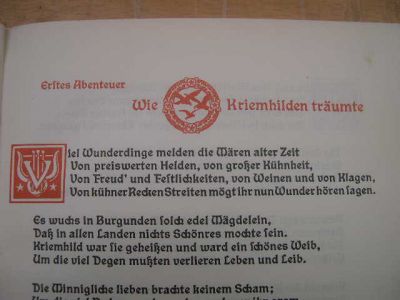
Überarbeitete Neuedition – wieviel ändern? (war: Warum sieht
Spin-Off aus dem Diskussionsstrang »warum sieht die fraktur aus, wie sie aussieht?«
Aber meine Ansicht: Ein Text aus der Zeit, in der Fraktur üblich war, sollte (wenn er es denn überhaupt wert ist) auch im Original zugänglich bleiben. Klar wird bei zunehmendem Zeitabstand die Frage immer wichtiger, wo eine "behutsame" Überarbeitung (so bezeichnet in üblichen Vorwortformulierungen) nötig ist, um eine normale Rezeption zu ermöglichen. Aber dann müssen doch weiterreichende Änderungen erwogen werden als ein Wechsel des Fonts. Und dazu ist eine profunde Kenntnis der Regeln der Zeit erforderlich.
Schön, dass dieses Thema hier einmal zur Sprache kommt (vielleicht könnte man die Diskussion auch separat weiterführen?). Hier wird oft von der »Zeit, in der Fraktur üblich war« gesprochen – gemeint ist aber vornehmlich die Zeit von ca. 1800 bis zum Frakturverbot. Diese Texte sind für uns ja – Fraktur hin oder her – in der Regel noch ohne weiteres verständlich. Aber was ist mit einem Text aus dem Mittelalter? dem Barock? Lesen die Original-Fetischisten hier tatsächlich auch ihren Machiavelli, ihren Shakespeare, ihren Molière oder Calderón ›im Original‹?
Der durchschnittliche Leser macht sich in der Regel überhaupt keine Vorstellung, welch gewaltige Arbeit hinter einer Neuedition älterer Texte – mein Alltag übrigens – steckt. Gerade das Problem des ›Original‹ – ob Buch oder Musik – ist weitaus komplizierter, als es auf den ersten Blick scheint: In der Regel hat man ja verschiedene Versionen, Lesarten, Textstufen, Ausgaben, Varianten etc. – die Frage nach dem Layout oder der Schrifttype ist da noch eine der einfachsten.
Schön, dass dieses Thema hier einmal zur Sprache kommt (vielleicht könnte man die Diskussion auch separat weiterführen?). Hier wird oft von der »Zeit, in der Fraktur üblich war« gesprochen – gemeint ist aber vornehmlich die Zeit von ca. 1800 bis zum Frakturverbot. Diese Texte sind für uns ja – Fraktur hin oder her – in der Regel noch ohne weiteres verständlich. Aber was ist mit einem Text aus dem Mittelalter? dem Barock? Lesen die Original-Fetischisten hier tatsächlich auch ihren Machiavelli, ihren Shakespeare, ihren Molière oder Calderón ›im Original‹?
Der durchschnittliche Leser macht sich in der Regel überhaupt keine Vorstellung, welch gewaltige Arbeit hinter einer Neuedition älterer Texte – mein Alltag übrigens – steckt. Gerade das Problem des ›Original‹ – ob Buch oder Musik – ist weitaus komplizierter, als es auf den ersten Blick scheint: In der Regel hat man ja verschiedene Versionen, Lesarten, Textstufen, Ausgaben, Varianten etc. – die Frage nach dem Layout oder der Schrifttype ist da noch eine der einfachsten.
Mich interessiert dieses Thema auch sehr. Wobei ich interessierter Laie bin und nicht in der Lage, die von Dir angesprochenen Texte wissenschaftlich fundiert zu lesen.
Aber ich weiß definitiv durch eigene Anschauung, daß - einmal weitläufig Belletristik genannt - viele solche Werke aus der Zeit des 19. und 20. Jahrhunderts in Neuauflagen textlich "behutsam dem Verständnis unserer modernen Zeit angespaßt wurden". Hierüber mag man noch trefflich streiten können.
Ärger und als nicht akzeptabel empfinde ich es, wenn es um geschichtliche Texte geht. Diese sollten, so meine ich, unverändert bleiben. Einfach, weil sie nicht nur die Fakten aus Sicht des jeweiligen Historikers seine Epoche wiedergeben und damit auch eine wichtige Einsicht in das von ihm vertretene Sittenbild (kein Historiker ist in der Lage, Fakten ohne Interpretation aufzuzählen. Es machte auch keinen Sinn.).
Naturgemäß habe ich als Laie aber z.B. Probleme, Texte, die von Wallenstein geschrieben wurden oder von Zeitgenossen über ihn (und das fast immer 50-100 Jahre nach seinem Tod) zu verstehen.
Als wohltuend empfinde ich dann Historiker wie Golo Mann, die die Inhalte in auch für mich verständlichem Deutsch formulieren, aber ungemein oft dann halt auch die Original-Zitate aus den entsprechenden Schriften hinzufügen. Das gibt mir zumindest ein Gefühl der Kontrolle, ob das von ihm Formulierte dem Text entspricht. Bzw. es baut bei mir Vertrauen zum Autor selbst auf, so daß ich dessen Interpretationen auch als gegeben hinnehme.
Überhaupt ist ein solcher Text auch für den Laien nur verständlich, wenn er sich zunächst mit dem Umfeld, in diesem Fall von Wallenstein, beschäftigt. Nur so gibt es die Möglichkeit, vom hohen Roß des heute Lebenden, der durch den zeitlichen Abstand eben auch die nachträgliche Entwicklung kennt, in die damalige Zeit einzutauchen und wenigstens einen Hauch davon zu verstehen und zu würdigen, wie jemand damals gedacht und empfunden hat.
Autoren von Werken zur Historie, aber auch zur Musik und zur Kunst interrpetieren mir zu stark. Biegen oft genug den Standpunkt desjenigen, über den sie schreiben, in vorbeugender Policital Correctness um. Das empfinde ich als illegitim und verwerflich.
Teile dieser Literatur durften publiziert werden, nachdem sie "überarbeitet und den Grundsätzen des Re-Education-Programmes entspachen". Andere nicht. Erst sehr seit einigen Jahren gibt es Reprints diverser Werke, also keine überarbeitete Neuauflagen, sondern Faksimile-Drucke z.B. vom Berg-Verlag.